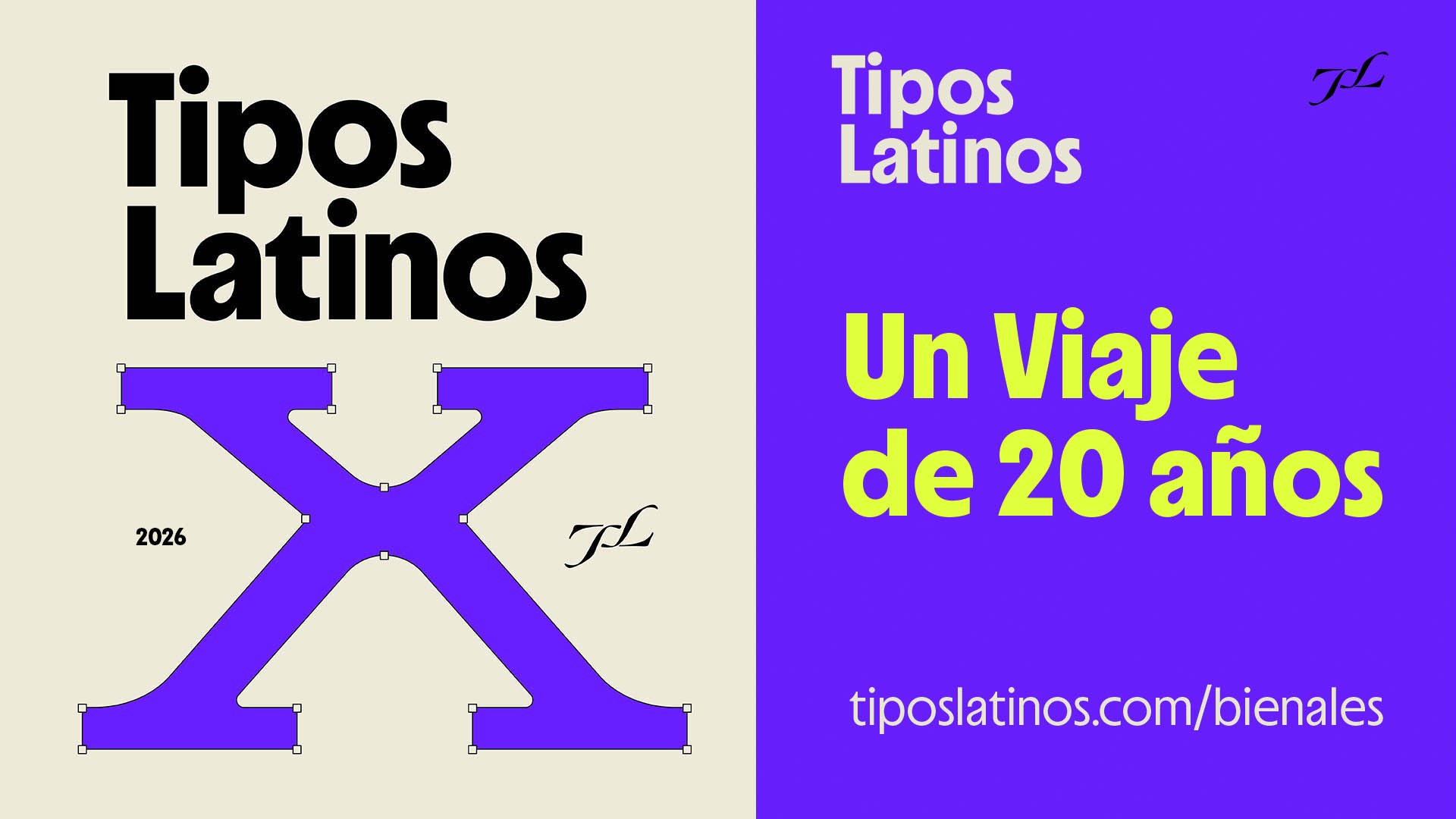
Nuestro registro histórico: Veinte años de tipografía latinoamericana
Tipos Latinos invita a realizar un recorrido por cada una de sus nueve ediciones en la sección “Bienales” de su página web.
Con motivo de la décima edición de la bienal Tipos Latinos, la organización se ha dedicado a compilar y hacer accesible en su sitio web la información relevante de las nueve ocasiones previas, realizadas desde el año 2004.
En la sección "Bienales" se ofrece información detallada online que incluye: miembros del jurado (Jura), los proyectos seleccionados con sus respectivas imágenes y fichas de identificación (Resultados), las cifras clave (Estadísticas) y la programación (Agenda). En esta sección es posible consultar la conformación del Comité Regional, las síntesis curriculares de los jurados, las imágenes de los proyectos elegidos con sus respectivas fichas de identificación, y el análisis estadístico desglosado tanto por categorías como por países.
Esto representa el registro histórico de los últimos 20 años de la tipografía latinoamericana reflejada en la Bienal que nació en Argentina en 2004 como “Letras Latinas”, título que ostentó hasta la segunda edición, realizada en el 2006. A partir de la tercera, pasó a denominarse Tipos Latinos.
La idea de la sección “Bienales” es que se convierta en un repositorio informativo referencial para docentes y diseñadores interesados en el desarrollo de la Tipografía en nuestra región.